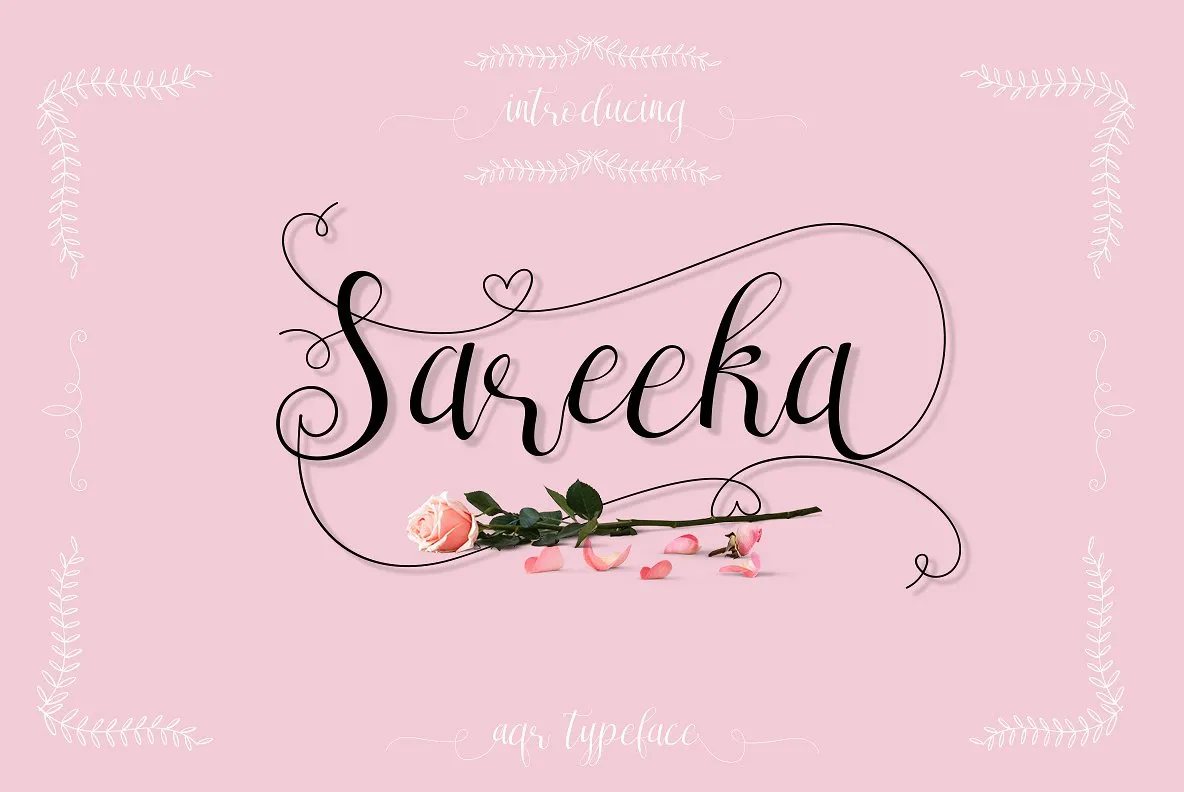
Sareeka Script Font – Download Grátis
Sareeka é uma tipografia de calligrafia moderna com mais variações estilísticas e muitos recursos. Esta fonte foi criada para abraçar a elegância feminina, sendo perfeitamente adequada para design de roupas, eventos de casamento, convites de casamento e outros desafios gráficos que você possa ter em mente. Com Sareeka na sua mesa de trabalho, está mais perto de transformar suas ideias inspiradoras em realidade com um toque único e sofisticado. Seja para criar uma identidade visual única ou personalizar um convite de casamento, a sutil elegância do Sareeka atenderá as necessidades de design que você possa ter.